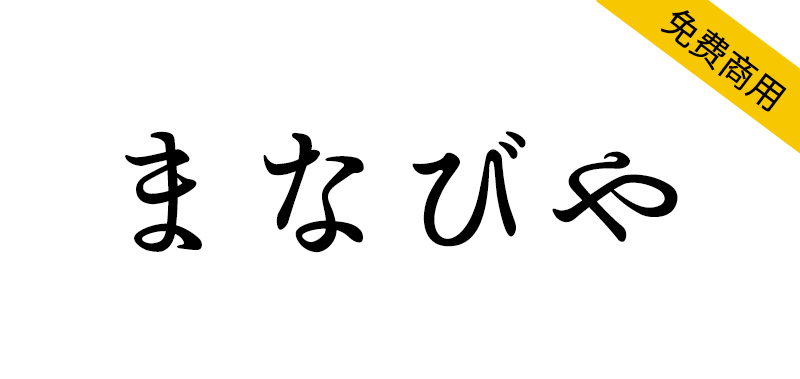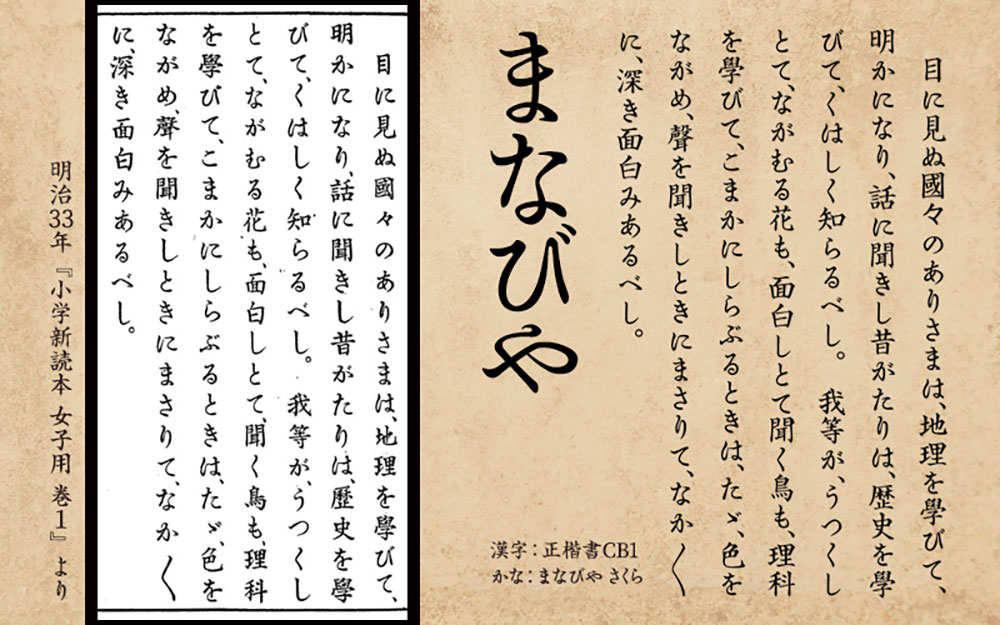
まなびや(Manabiya)这是根据明治时代的教科书创建的平假名字体。
*出处:国立国会图书馆数字馆藏
文学社编辑部编《新小学读物:女生专用第1卷》文学社(明治33年)
我创造了一些文本中没有的人物来配合气氛,或者用我自己独特的解释来创造它们。
这是仅适用于平假名和片假名的字体。
有两种类型:ICHO与SAKURA
明治時代の教科書を元に作成したひらがなフォントです。
※資料:国立国会図書館デジタルコレクション
文学社編輯所 編『小学新読本 : 女子用 巻1』文学社(明治33年)
文中になかったいくつかの文字は雰囲気を合わせて作ったり、かなり独自の解釈で作成しています。
ひらがな・カタカナのみのフォントです。
ノーマルな『さくら』と、
古めかしい感じにガタガタしている『いちょう』の2種があります。
注:这款字体可以和源流明体、源云明体、英椎楷书搭配使用效果更佳